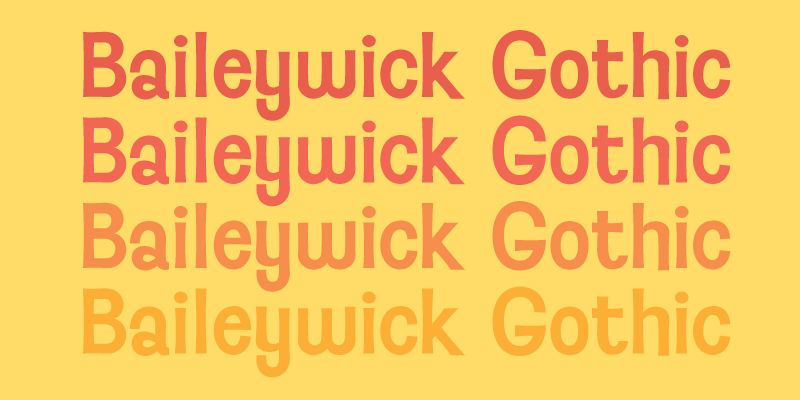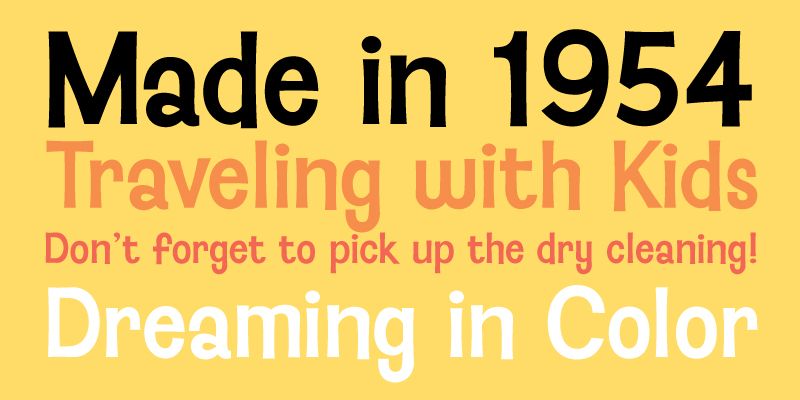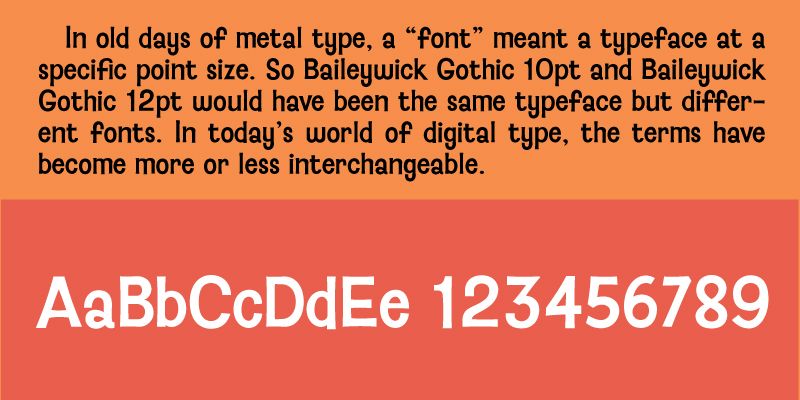
Baileywick Gothic est une police sans empattement originale de Jukebox qui dénote une exubérance empreinte d’optimisme. La ligne de base légèrement modulée et la grande hauteur d’œil la rendent agréable pour les yeux.
Jukebox est le fruit des efforts de Jason Walcott, concepteur typographique de longue date. Jason a conçu sa première police de caractères appelée « Holiday Times » à l’automne 2000, ce qui a marqué le début d’un long et merveilleux voyage qui a conduit au Jukebox d’aujourd’hui.
Après avoir conçu cinq ou six polices de caractères supplémentaires, Jason a commencé à vendre ses caractères sur MyFonts.com à l’été 2001. À l’époque, sa fonderie était dénommée « JAW Fonts ». Plusieurs de ses modèles sont rapidement devenus populaires sur MyFonts.com et les ventes ont augmenté jusqu’à la fin de 2002.
Début mars 2003, Walcott a reçu un appel téléphonique de la société Veer Inc., alors en pleine expansion, qui souhaitait proposer sa bibliothèque de polices de caractères qui se composait alors d’une cinquantaine d’éléments. L’accord conclu avec Veer a donné naissance à une toute nouvelle aventure et JAW Fonts a mis la clé sous la porte, pour être réorganisée et relancée sous le nom de Jukebox en juin 2003. Produit exclusif de Veer de 2003 à 2015, Jukebox est devenu l’une des normes de l’industrie dans les bibliothèques typographiques disponibles. Les polices Jukebox ont été utilisées pour d’innombrables produits et modèles, films, livres, productions télévisées et plus encore, par des sociétés comme Disney, HGTV, The Food Network, les parcs d’attraction Disney, Hershey’s, VistaPrint et bien d’autres. En 2011, la famille de polices Eloquent de Jason a reçu le prix de la Meilleure conception de police de caractères de la part du magazine Communications Arts Magazine dans le cadre de sa compétition annuelle qui récompense les plus belles typographies.
Le 31 mars 2016, Veer a définitivement déposé le bilan et la sélection de la bibliothèque Jukebox est revenue à Jason, qui veille à ce que Jukebox continue de fournir au monde du design des typographies professionnelles et de haute qualité.